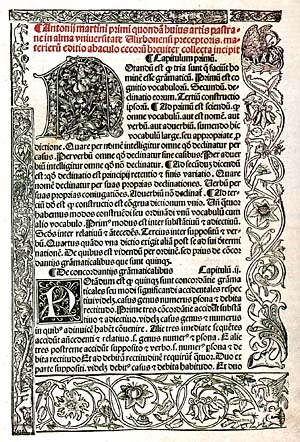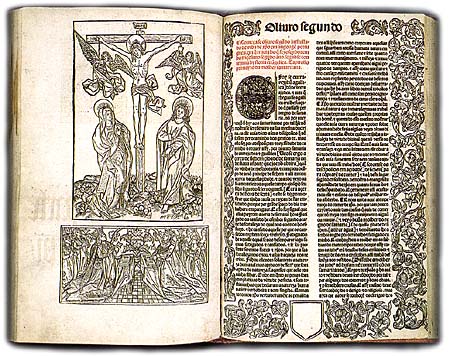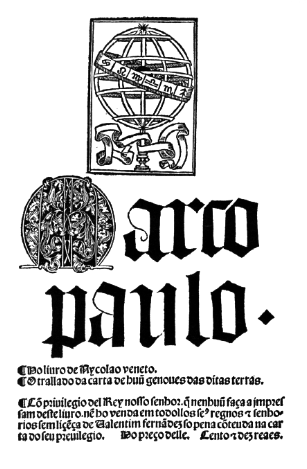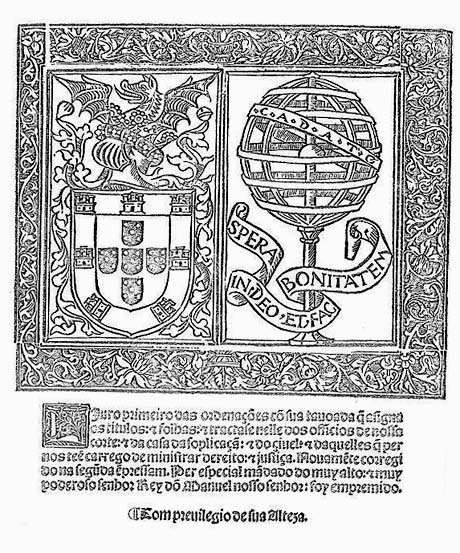
Valentim Fernandes (? - 1519)ou Valentin Ferdinand, Valentim Fernandes da Morávia A figura mais destacada da Prototipografia em Portugal. Este impressor alemão obteve privilégios de impressão em Portugal a partir de 1495. Hoje conhecemos 18 livros por ele impressos, 6 dos quais foram produzidos no século xv.
Quando se estabeleceu em Portugal, Valentim Fernandes dominava o alemão, o latim, o toscano, o castelhano e o português, conhecimentos que pode ter adquirido em viagens pela Europa. Foi tradutor e autor; foi também mercador, investigador, historiador e geógrafo. Valentim Fernandes terá nascido na região da Morávia, zona de influência alemã, nas imediações da Boémia, com prelos a trabalhar desde a década de 1480. Em 1486, Conrad Stahel imprimiu na cidade de Brno o primeiro livro. Em 1493 VF esteve em Sevilha. VF chegou a Portugal provavelmente em 1493. De 1495 até 1516, este tipógrafo alemão obteve privilégios de impressão e exerceu em Portugal a indústria, servindo a rainha Dona Leonor, viúva de João II, de quem foi escudeiro. Hábil homem de negócios e humanista de cultura abrangente, é a Fernandes que devemos um dos mais importantes testemunhos sobre os Descobrimentos portugueses: as anotações manuscritas em cerca de 300 páginas, que hoje estão guardadas na Staatsbibliothek München, designadas por Manuscrito de Valentim Fernandes. No ano de 1503 teve a sua nomeação como corretor do mercado de Lisboa para as transacções de especiarias ultramarinas destinadas à Alemanha e de notário (ou tabelião) para os contratos dos comerciantes alemães entre si. Vita Christi, 1495Com oficina tipográfica em Lisboa, Valentim Fernandes foi o primeiro a imprimir livros ilustrados em Portugal. A Vita Christi é um dos mais importantes incunábulos (livros impressos até 1500) impressos em Portugal. Em quatro partes in-folio impressas em Lisboa, em 1495, por ordem
e a expensas do rei João II e de D. Leonor, é considerado o
terceiro incunábulo português, depois do
A impressão foi executada em parceria com Nicolau da Saxónia, um impressor alemão que chegara a Portugal vindo de Espanha. Curiosamente, a divisa da Raínha, o camaroeiro, ficou impressa de forma invertida. Para imprimir a obra, Valentim Fernandes teve de comprar papel no estrangeiro e usar tipos móveis do mestre alemão Pedro Brun, tipógrafo activo em Sevilha, além da grande gravura do Calvário, atribuída ao mestre E. S., um dos mais importantes gravadores alemães do século XV. A letra maiúscula E tem uma forma que só aparece em Sevilha, nas oficinas de Pedro Brun, de Meinard Ungut e Stanislau Polono, bem como na casa de impressão dos chamados Companheiros Alemães, todos em actividade em 1495.
Vespasiano, 1496O segundo livro ilustrado impresso por VF é a Estoria de muy nobre Vespesiano emperador de Roma, que saiu do prelo em Lisboa, em 1496; as gravuras são de origem alemã. Em 20 de Abril de 1496, foi concluída a impressão desta novela de cavalaria, obra em língua portuguesa. Neste mesmo ano (1496), VF imprimiu o Regimento proueytoso contra a pestenença, uma tradução feita pelo padre franciscano Luís de Rás, do original de Johan Jacme. Grammatica PastraneO terceiro livro ilustrado de Valentim Fernandes é a Grammatica Pastrane. No ano de 1497 imprimiu três opúsculos que viriam a formar a Grãmatica Pastrane, texto latino mas que contém algumas frases em português. Desta obra fazem parte o Thesaurus Pauperum, cuja impressão não está datada, as Materiae de Pedro Rombo, adaptação do texto de Juan Pastrana, aí designado por Baculum Caecorum, acabadas de imprimir em 27 de Maio de 1497, e as Materiae de António Martins, sinopse do texto de Pastrana, cuja impressão terminou em 20 de Junho daquele ano. Em 21 de Fevereiro de 1500 VF terminou a impressão da
1.ª parte das Epistole et Oratines, de
Em 1501, em 10 de Abril, o impressor terminou a execução da obra Glosa famosissima sobre las Coplas de dõ Jorge Marriq, de Alonso de Cervantes e, talvez, os Proverbios de Iñigo Lopez de Mendoza, ambas obras impressas em língua espanhola. Relatos de viagensEm 1502, Valentim Fernandes deu à estampa três relatos de viagens:
Com o livro de Marco Paulo, Valentim Fernandes iniciou a divulgação impressa de assuntos ultramarinos. Se Valentim Fernades foi ou não o tradutor do relato de viagens de Marco Paulo do latim em português, é uma opinião discutida entre os historiadores; mais provável é que tenha traduzido do toscano o relato das viagens de Nicolao Conti, escritas por Poggio. Em 1502 Valentim Fernandes imprimiu os Poemata de Cataldo Sículo. Em 21 de Fevereiro de 1503, Valentim Fernandes é nomeado pelo rei Manuel I para o cargo de corrector dos mercadores de Lisboa, com funções de tabelião. Nos primeiros anos do século XVI, Fernandes poderá ter pensado publicar uma obra de sua autoria, sobre as viagens marítimas e os descobrimentos portugueses. Este propósito explicaria a metódica investigação à qual se dedicou de 1506 a 1510, quando a peste grassava em Lisboa e Fernandes se mudou para Tomar para escapar à epidemia. Fugindo da peste que se declarara em Lisboa em Outubro de 1505, Valentim Fernandes instalou-se em Tomar e só voltou a Lisboa em 1511. Entrevistando marinheiros e viajantes, recolheu um sem número de informações em primeira mão. Valentim Fernandes anotou um extenso material sobre as ilhas atlânticas e os novos territórios africanos descobertos pelos portugueses, escritos esses que ironia do destino! não ficaram entre nós, porque mais tarde foram entregues ao seu amigo, o humanista alemão Konrad Peutinger. Uma transcrição para texto impresso do famoso Manuscrito de Valentim Fernandes foi oferecida à Academia Portuguesa da História por Joaquim Bensaúde em 1940 (a leitura e a revisão das provas tipográficas fez António Baião). Valentim Fernandes colaborou com outros tipógrafos estrangeiros, estabelecidos em Portugal:
Em 1504, três livros saem do prelo de Valentim Fernandes:
Em 16 de Dezembro conclui no entanto a impressão dos Autos dos Apostolos, continuação do texto da Vita Christi. Durante a epidemia de peste, Valentim Fernandes parece ter feito um interregno na sua actividade de impressor. Regressado a Lisboa, retoma a sua actividade de tipógrafo e
imprime, provavelmente em 1510 ou 1511, uma versão portuguesa dos
Evangelhos e Epístolas, de Guilherme de Paris. Esta
edição de Valentim Fernandes é uma cópia literal da
impressão feita pelo impressor As Ordenações (1510-1514)Pouco depois de 1510, VF foi encarregado por Manuel I de imprimir as Ordenações do reino de Portugal. VF imprimiu estas Ordenações, em cinco volumes uma monumental codificação do ordenamento jurídico manuelino.
Mil exemplares de cada corpo, num total de 5000 volumes, custaram
a avultada soma de 700 mil réis. Valentim Fernandes dividiu o trabalho
de impressão com Ao contratar João Pedro de Cremona, recomendou-lhe Valentim Fernandes que fizesse uma tiragem especial em pergaminho destinada a D. Manuel I. A impressão destas Ordenações, relata o historiador Artur Anselmo nas suas Origens da Imprensa em Portugal, levou até final do ano 1514. Repetiu-se a impressão dos livros I e II, para fazer a dita tiragem em pergaminho, a fim de completar a colecção especial destinada a D. Manuel I. A impressão dos dois primeiros volumes foi lenta, por motivos que se desconhecem, mas que talvez se prendam com a complexidade do trabalho gráfico a executar e com a necessidade de uma cuidada revisão dos textos. O livro I, com 129 fólios, acabou de ser impresso em 17 de Dezembro de 1512. O livro II, com 60 fólios, ficou pronto em 18 de Novembro de 1513. Talvez por verificar que não conseguia cumprir o prazo acordado para a impressão da obra, decidiu Valentim Fernandes dar de subempreitada o resto da obra ao tipógrafo italiano João Pedro Buonhomini de Cremona, que viria a dar à estampa a edição especial em pergaminho de todos os 5 livros das Ordenações, destinada a Manuel I. A obra foi completada em 1514, sendo os dois primeiros livros executados por Valentim Fernandes e os outros três por João Pedro de Cremona. A última faseDe 1513 ou 1514, VF imprime a segunda parte das Epístolae et Orationes e das Visiones, duas obras de Cataldo Sículo. Em 1513 (?) o piemontês Nicolau Gazini veio de Espanha para Portugal. Gazini imprimiu em Lisboa, em conjunto com Valentim Fernandes, e em Março de 1518 deu à estampa um manual de sacramentos segundo o costume da igreja de Coimbra, Manuale secundum consuetudinem almae Colymbriensis ecclesiae, impresso com material tipográfico de VF. Em 1515, Valentim Fernandes imprime uma gramática de
Estevão Cavaleiro, a Ars Virginis Mariae e, em
associação com Reportorio dos TemposEm 1518, imprime o Reportorio dos têpos,
versão portuguesa feita pelo próprio Valentim Fernandes do
original castelhano de André de Li. O Reportorio dos
Tempos é uma compilação baseada em trabalhos de
Em 1496 tinha sido editada em Leiria a primeira obra de Astronomia impressa em Portugal, o Almanach Perpetuum Celestium Motuum de Abraão Zacuto, que originou todas as posteriores tábuas de declinação utilizadas na navegação. Trata-se de um livro muito raro, que foi mandado reproduzir por fotogravura em 1915 por Joaquim Bensaúde. Julga-se que Valentim Fernandes terá morrido pouco tempo depois da impressão do Reportório. Valentim Fernandes faleceu em 1518 ou em 1519. þ Fontes digitaisValentim: uma fonte OpenType, de Paulo Heitlinger Temas relacionadosSobre a Protipografia portuguesa:
BibliografiaAdalgisa Botelho da Costa. O Reportorio dos Tempos de André do Avelar e a astrologia em Portugal no século XVI. Dissertação de Mestrado defendida em 2001. Programa de Estudos Pós-Graduados em História da Ciência, PUC/SP . Códice Valentim Fernandes / Leitura paleográfica, notas e índice José Pereira da Costa ; pref. Joaquim Veríssimo Serrão ; ed. Academia Portuguesa da História. - Lisboa : A.P.H., 1997. - XXXI, 394, [1] p., [41] p. il. : il. ; 30 cm. - "Manuscrito Valentim Fernandes" oferecido à A.P.H. por Joaquim Bensaúde. Description de la côte occidentale d'Afrique (Senegal au Cap de Monte Archipels) / Valentim Fernandes, M. M. Sarmento Rodrigues (prof.). - Bissau : Centro de Estudos da Guiné Portuguesa, 1951. - 223 pp. . - Centro de Estudos da Guiné Portuguesa. 11) Jüsten, Helga Maria. Valentim Fernandes e a literatura de viagens, Universidade Aberta, 1999. Artur Anselmo. Tipografia e Filologia: A edição da Vita Christi impressa em Lisboa (1495) por Valentim Fernandes . Marília dos Santos Lopes. «Vimos oje cousas marauilhosas». Valentim Fernandes e os Descobrimentos Portugueses . Marion Ehrhardt. Frühe Deutsche Drucker in Portugal . João José Alves Dias. A primeira impressão das Ordenações Manuelinas, por Valentim Fernandes . História do mui nobre Vespasiano Imperador de Roma / nota prévia de Artur Anselmo. - Lisboa : Biblioteca Nacional, 1981. - [10], 81 p. : il. ; 21 cm. - fac-simile da ed. de Lisboa, de Valentim Fernandes, em 1496 31000 HIS HIS - 4879 Heitlinger, Paulo. Tipografia: origens, formas e uso das letras. Copyright © 2006 Paulo Heitlinger, ISBN 10 972-576-396-3 , ISBN 13 978-972-576-396-4, Depósito legal 248 958/06. Dinalivro. Lisboa, 2006. |